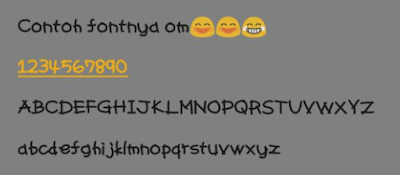
5 Font Xiaomi Mtz Terkeren dan Terbaik Paling Banyak Dicari
5 Font Xiaomi Mtz Terkeren dan Terbaik Paling Banyak Dicari - kubis.online Jika anda ingin mengubah tampilan font Xiaomi anda menjadi lebih keren, maka anda sudah mengunjungi halaman yang tepat.
Pada kesempatan kali ini saya akan kembali membagikan font Xiaomi pilihan yang paling banyak disukai belakangan ini.
| 5 Font Xiaomi Mtz Terkeren dan Terbaik Paling Banyak Dicari |
Rekomendasi font xiaomi ini tentu merupakan font mtz miui 11 dan font mtz miui 12 yang bisa anda download font xiaomi ini langsung di ponsel Redmi anda.
Pencil Font For Xiaomi Mtz
Font pertama yang saya bagikan disini adalah Pencil Font. Banyak pengguna Xiaomi yang menginginkan font ini mengingat tampilan dan design font yang cukup keren dan super elegan
Font FVGranada
Ini adalah font neo-grotesque kontemporer, bentuk fontnya memiliki style, enak dipandang dan tentunya tidak bikin sakit mata saat dibaca.
Font Acre Mtz
Font Acre masih bersaudara dengan font Sans Serif, yang memiliki tampilan seperti font keluarga Sans Serif.
Font San Francisco Pro Unicode MTZ
San Francisco Pro merupakan font bawaan dari handphone iPhone iOS 11 terbaru. Font ini memiliki gaya huruf bersih dan enak dilihat.
Font yang dikhususkan untuk perangkat Apple iPhone OS terbaru, kini bisa anda gunakan di hp Xiaomi Redmi OS MIUI.
Font San Francisco Pro Unicode MTZ adalah font yang sudah dimodifikasi agar mendukung simbol dan logo unicode untuk untuk pengguna OS MIUI.
Font Harmonia Sans
Sebetulnya Harmonia Sans merupakan font web, font khusus website. Namun, saya cukup tertarik untuk membuatnya menjadi font MIUI dan bisa digunakan di ponsel Xiaomi Redmi.
Harmonia Sans Unicode adalah font yang telah saya modifikasi agar supaya bisa membaca jenis simbol dan icon unicode, jadi teman-teman bisa menambahkan logo operator di status bar.